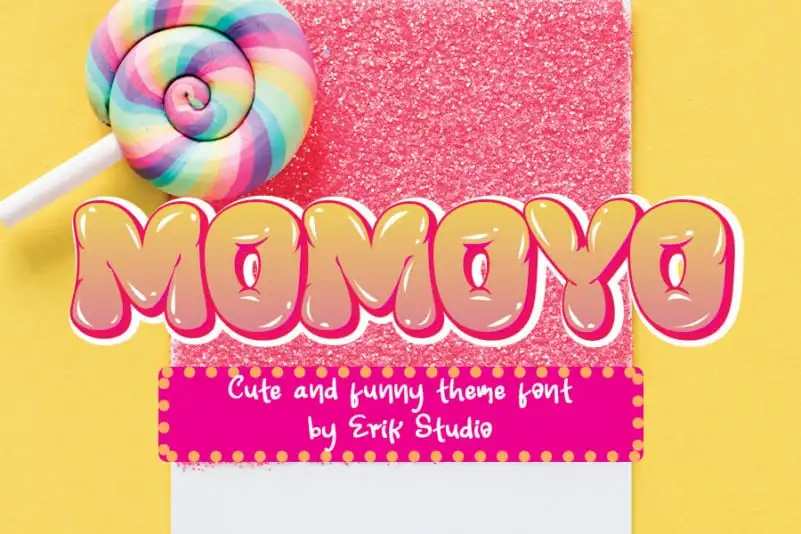
Descubra a Momoyo Display Font, uma elegante escolha para suas próximas criações digitais. Especificamente projetada para logos, identidades de marca e trabalhos DIY, essa fonte apresenta um estilo limpo com toques de personalidade única. Perfeita para dar um toque divertido e criativo a qualquer projeto que você esteja iniciando, seja em redes sociais ou em DIYs cheios de personalização. A Momoyo Display é uma fonte de display, que traz sua característica levemente irônica para as suas criações. Inspirada no design japonês com seus desenhos delicados e detalhes sutis, essa fonte pode dar ao seu projeto um toque único e moderno, tornando-a imediatamente chamativa e reconhecível. Seja você criando materiais de marketing, trabalhando em redes sociais ou fazendo DIYs cheios de personalidade, a Momoyo Display é uma excelente opção para trazer vida a suas criações digitais.